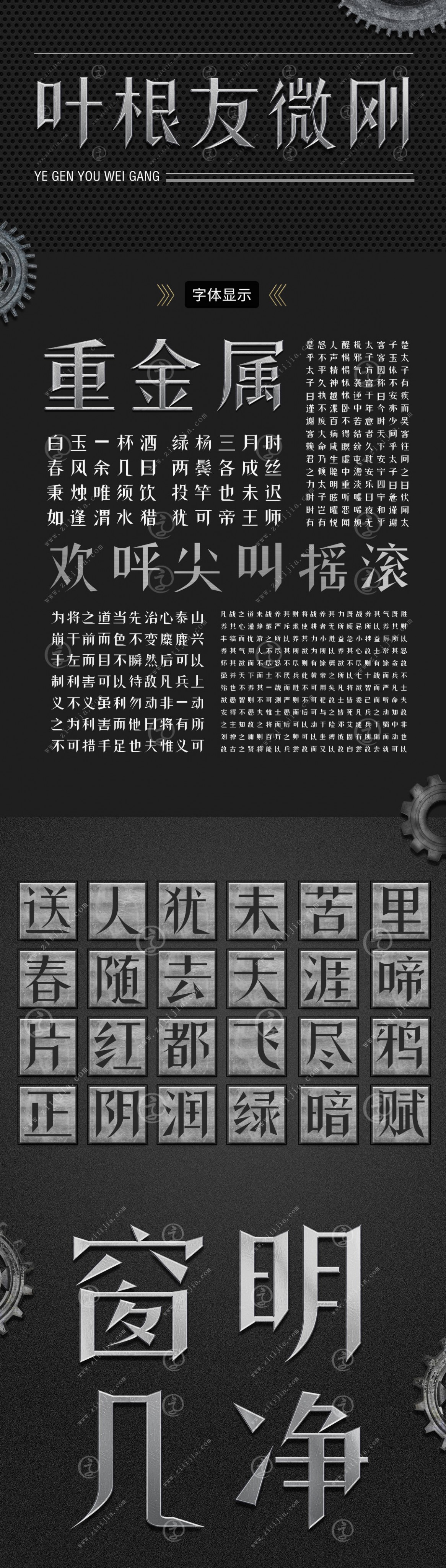
葉根友微剛
字體作者:葉根友
創(chuàng)作年代:2015年
字體介紹
2016年度最新發(fā)布的字體,該字體風格獨特,簡單大方而有銳氣,設計的理念來自竹林里砍竹子后的斜切面創(chuàng)意,利用這個創(chuàng)意應用在書法字體上,形成了較好的體現效果。在2016年發(fā)布的這么多字體中,小編最喜歡的就是這款字體了,很獨特的視覺沖擊效果,讓人一看就過目不忘這樣的字型。
創(chuàng)作記事
2014年6月,該字體的初步設計理念畫出
2014年8月,開始設計中文字形,三個月做了450個漢字
2014年12月,1200個漢字制作完畢
2015年3月,1800個漢字制作完畢
2015年8月,6763個漢字制作完畢
2015年10,最后微調
2015年12月,測試,并修正了部分字的筆畫和修改了赱之底的字形
2016年2月,正式發(fā)布